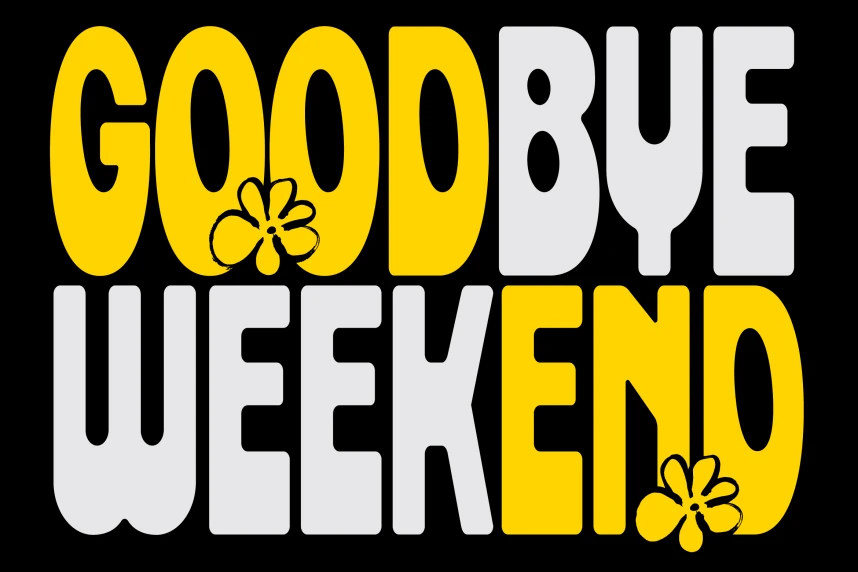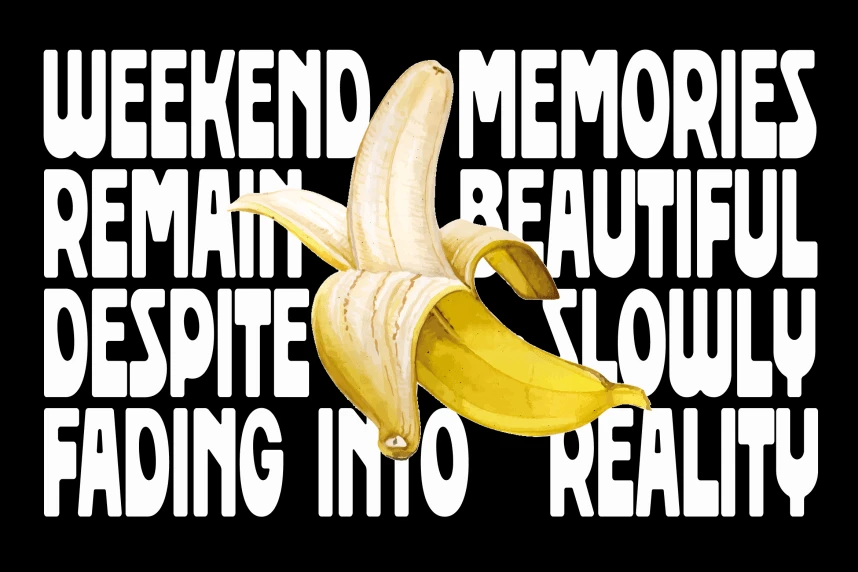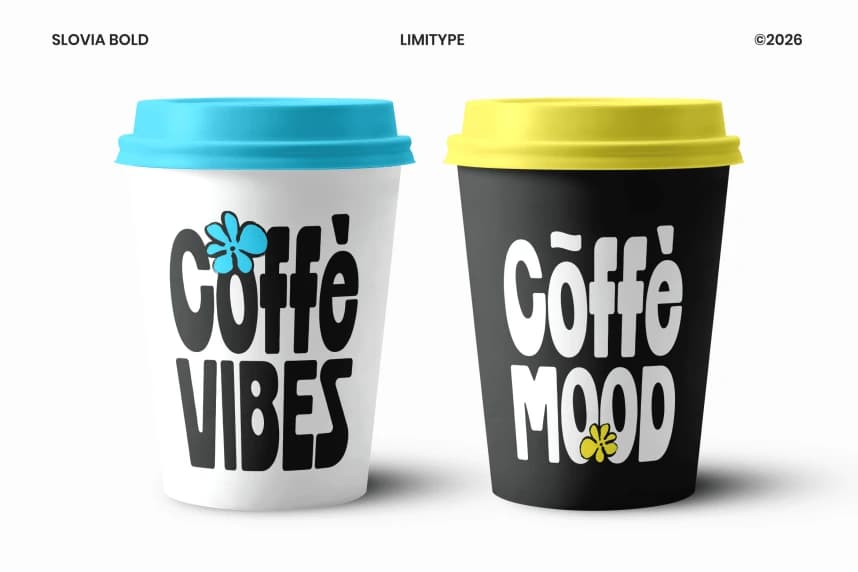
Slovia Font
Slovia Font, oyunbaz biçimler ve benzersiz bir karaktere sahip kalın sıkıştırılmış bir yazı tipidir; her tasarım projesine enerjik bir kişilik ve öne çıkan görsel çekicilik kazandırmak için tasarlanmıştır. Kendine özgü tarzı, modern yaratıcılığı güçlü bir yapı ile birleştirir.
Slovia Font, kalın sıkıştırılmış bir yazı tipi olup oyuncu biçimler ve benzersiz bir karaktere sahiptir; her tasarım projesine enerjik bir kişilik ve öne çıkan görsel çekicilik kazandırması için tasarlanmıştır. Özgün tarzı, modern yaratıcılığı güçlü bir yapı ile birleştirir.